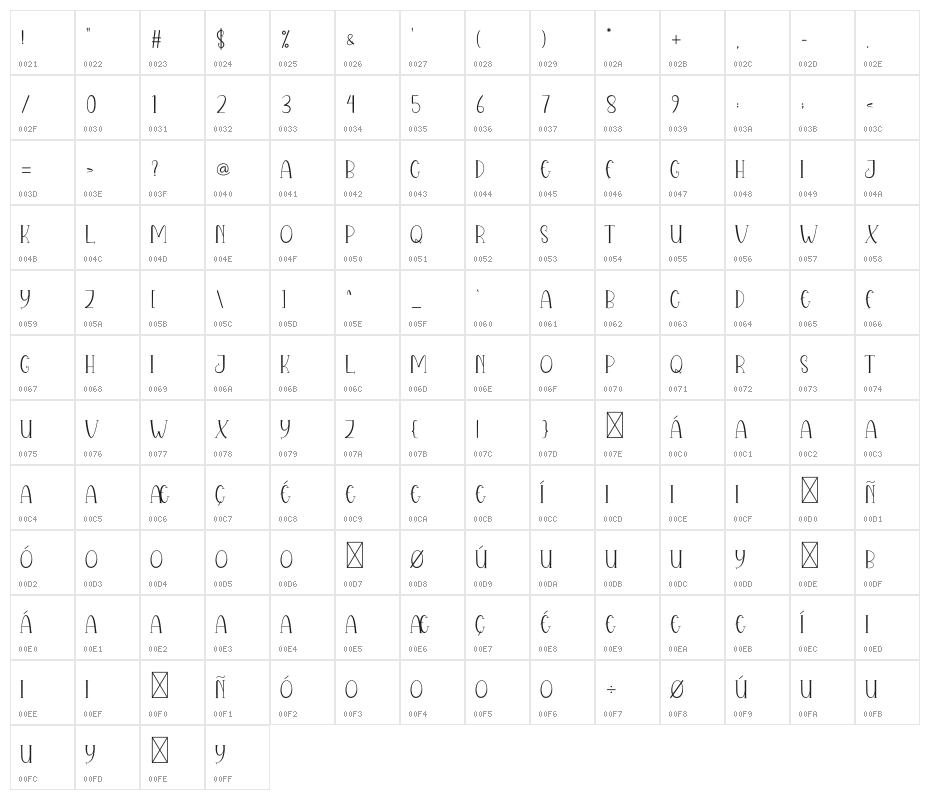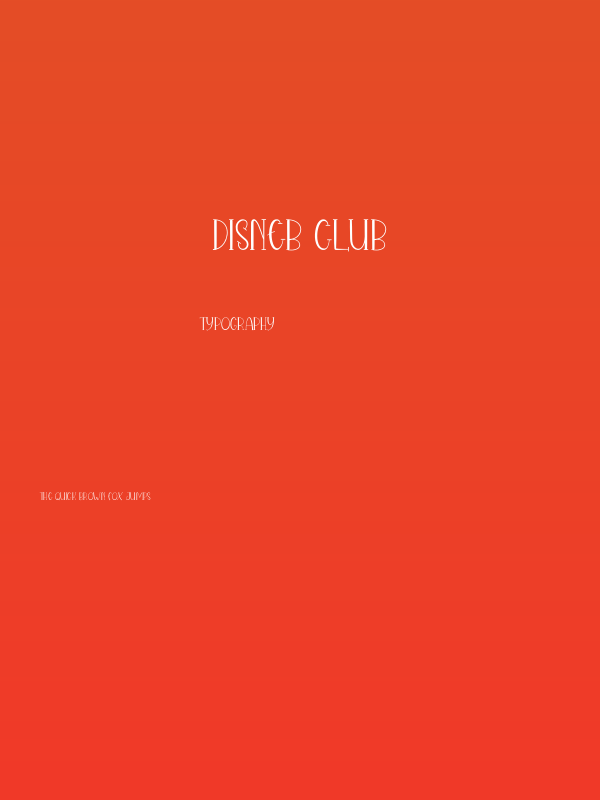
Disneb Club Font
| Stile generale | Playful and Decorative |
| Caso d'uso | Headlines, Logos, Creative Projects |
| Progetti proposti | Ideal for children's books, playful branding, party invitations, and creative posters. |